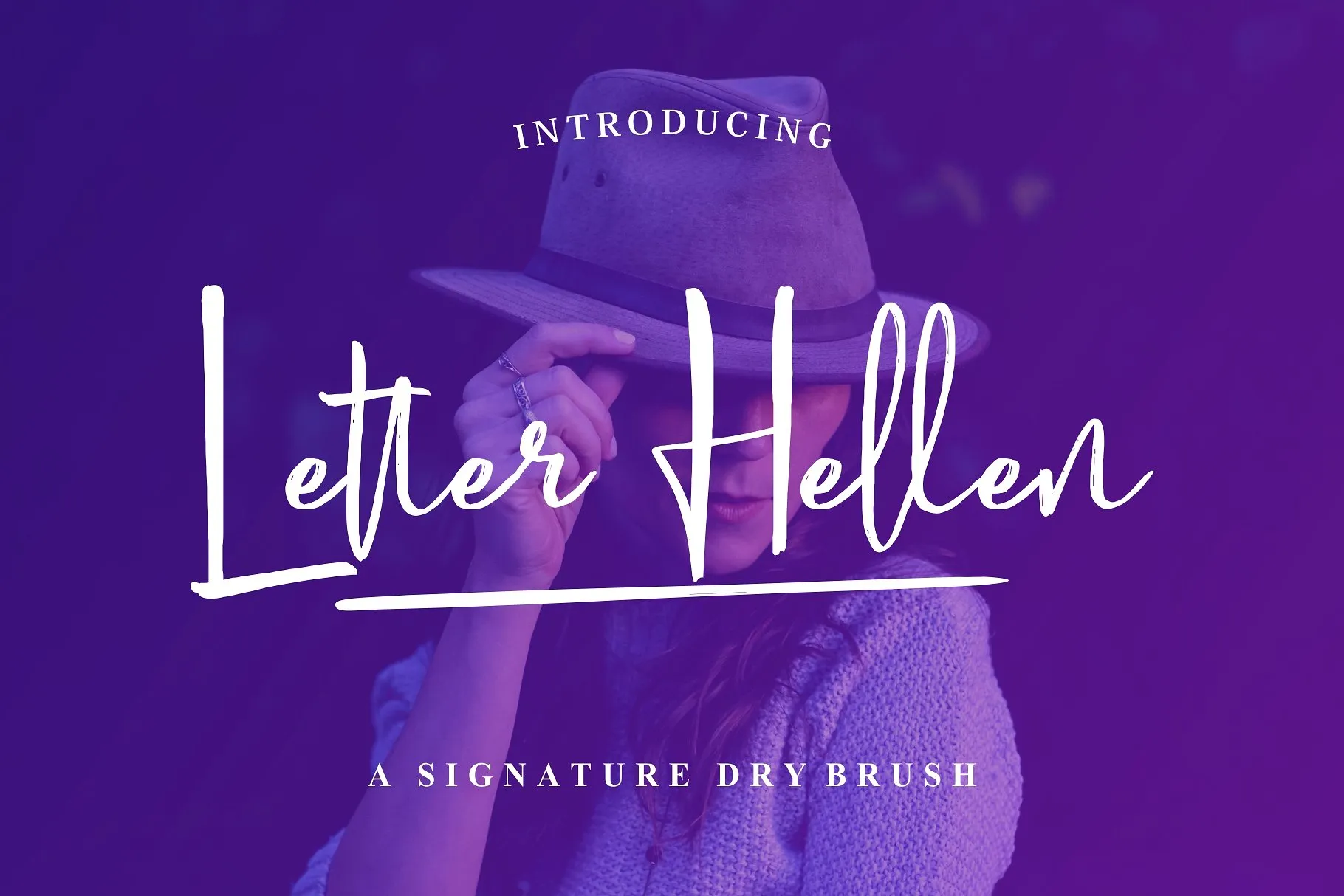
Letter Hellen Signature Font – Download Grátis
Esta é uma bela nova fonte de assinatura para design e artesanato, perfeita para projetos de qualquer tipo! Introduzimos a Fonte Letter Hellen. A Letter Hellen é um novo estilo de assinatura sem brilho com linhas elegantes, tornando-a ideal para criar sua marca pessoal em projetos variados como: logotipos, convites, material gráfico, designs casamentos, posts no redes sociais, anúncios, embalagens de produtos, design de produto, etiquetas, fotografia e marcas especiais. Este design se encaixa perfeitamente para qualquer projeto criativo em que você precise da sua personalidade e estética única. Descubra como pode transformar suas ideias digitais em algo único e atraente com a Letter Hellen Font!